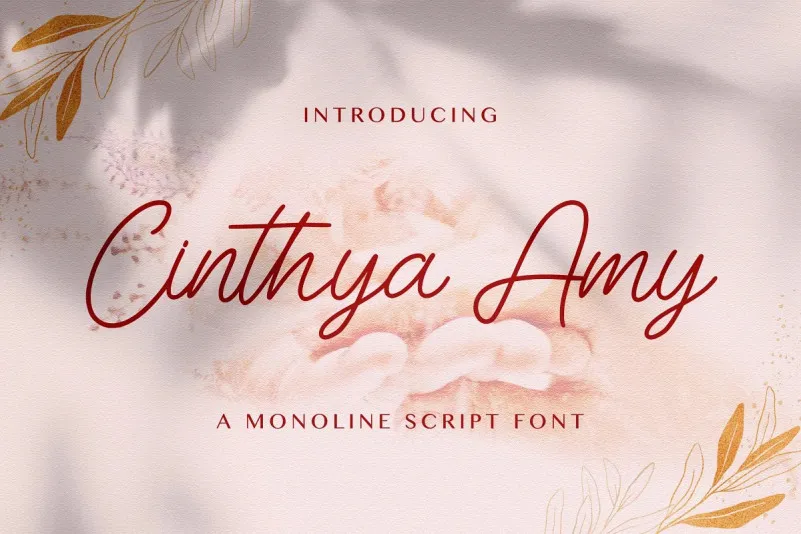
Cinthya Amy Handwritten Font – Download Grátis
A Cinthya Amy Handwritten Font é uma nova tipografia script monoline criada pela StringLabs, oferecendo um estilo elegante e sofisticado. Com caracteres belos e bem equilibrados, a Cinthya Amy Handwritten Font se adapta perfeitamente a um vasto número de projetos. Este tipo de fonte é ideal para quem busca uma mão escrita cuidadosamente elaborada que pode ser usada em criações inovadoras. Experimente adicioná-la aos seus ideais mais criativos e observe como ela os torna ainda mais vivos!